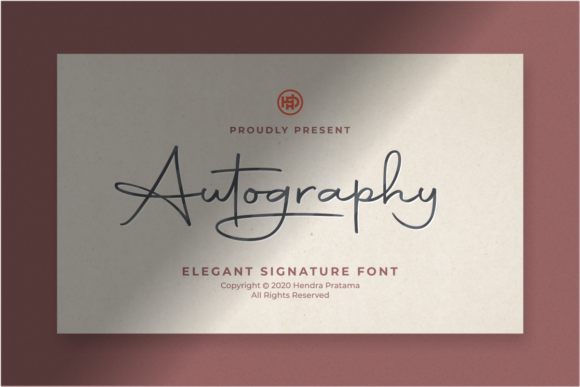
Autography
POD(์ฃผ๋ฌธํ˜• ์ธ์‡„) ์ œํ’ˆ, ๊ฒฐํ˜ผ์‹ ์ดˆ๋Œ€์žฅ ๋˜๋Š” ์†Œ์…œ ๋ฏธ๋””์–ด ๊ทธ๋ž˜ํ”ฝ์„ ๋งŒ๋“ค ๋•Œ Autography๋Š” ์ด์ƒ์ ์ธ ์„ ํƒ์ž…๋‹ˆ๋‹ค.